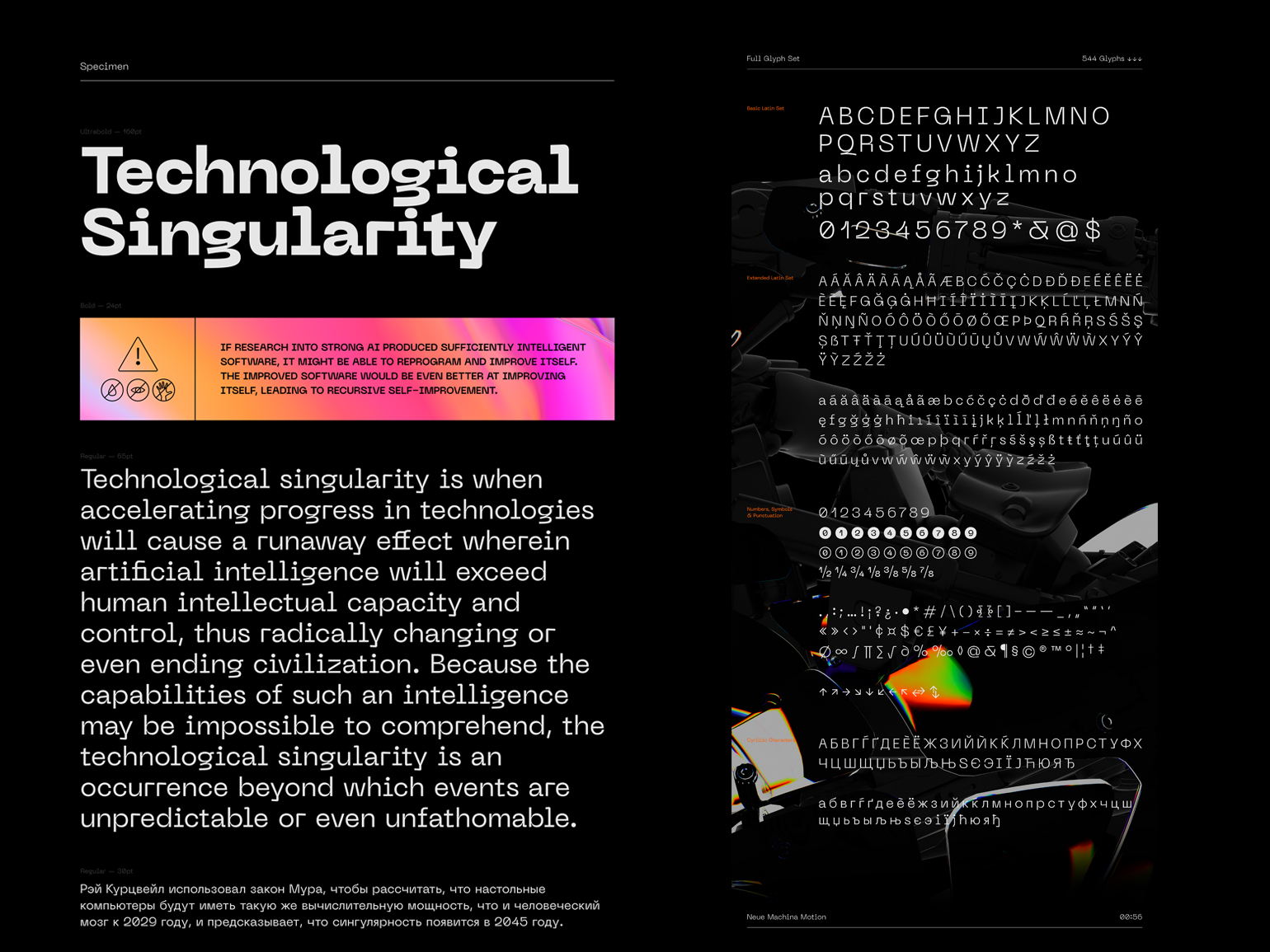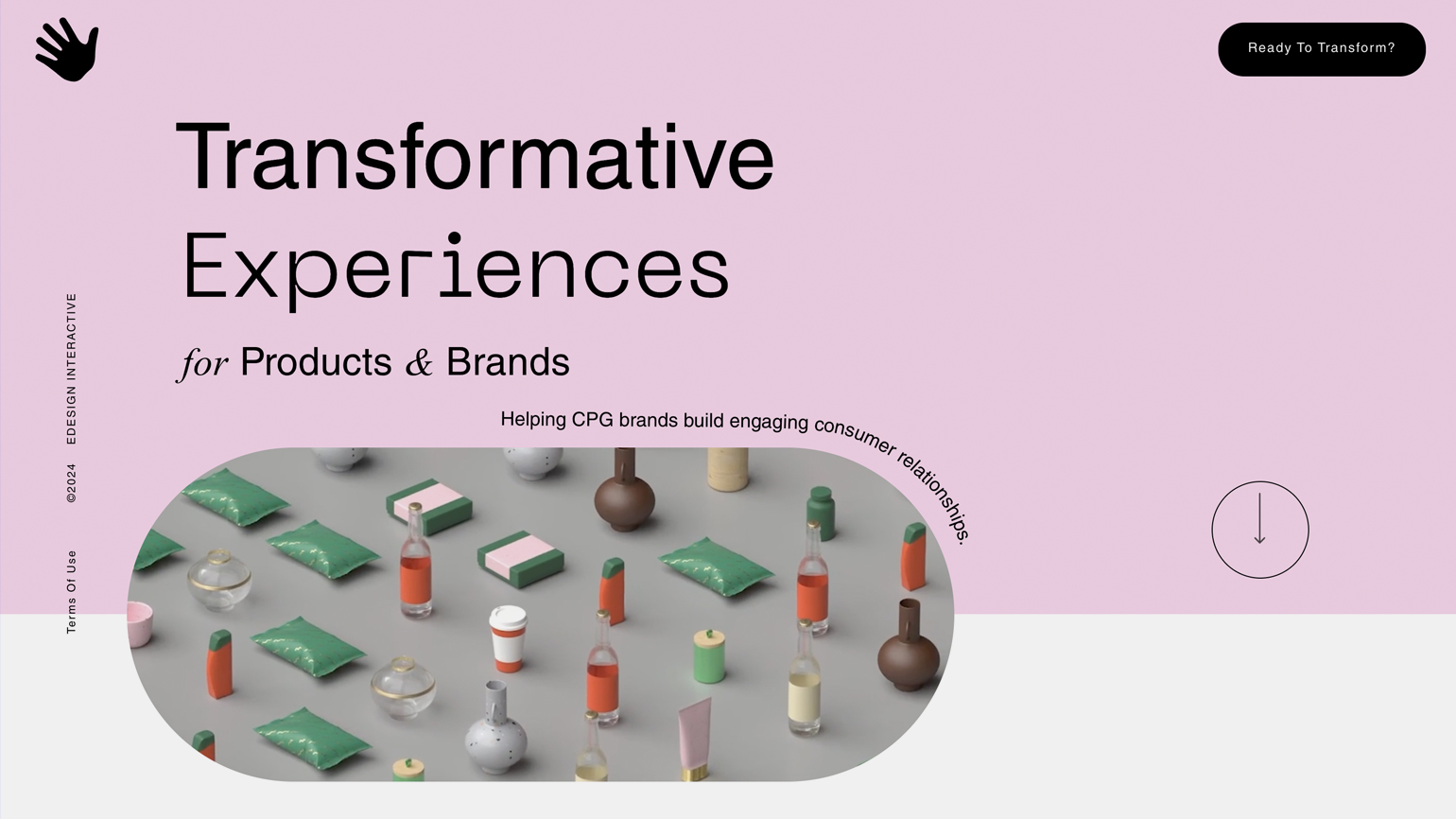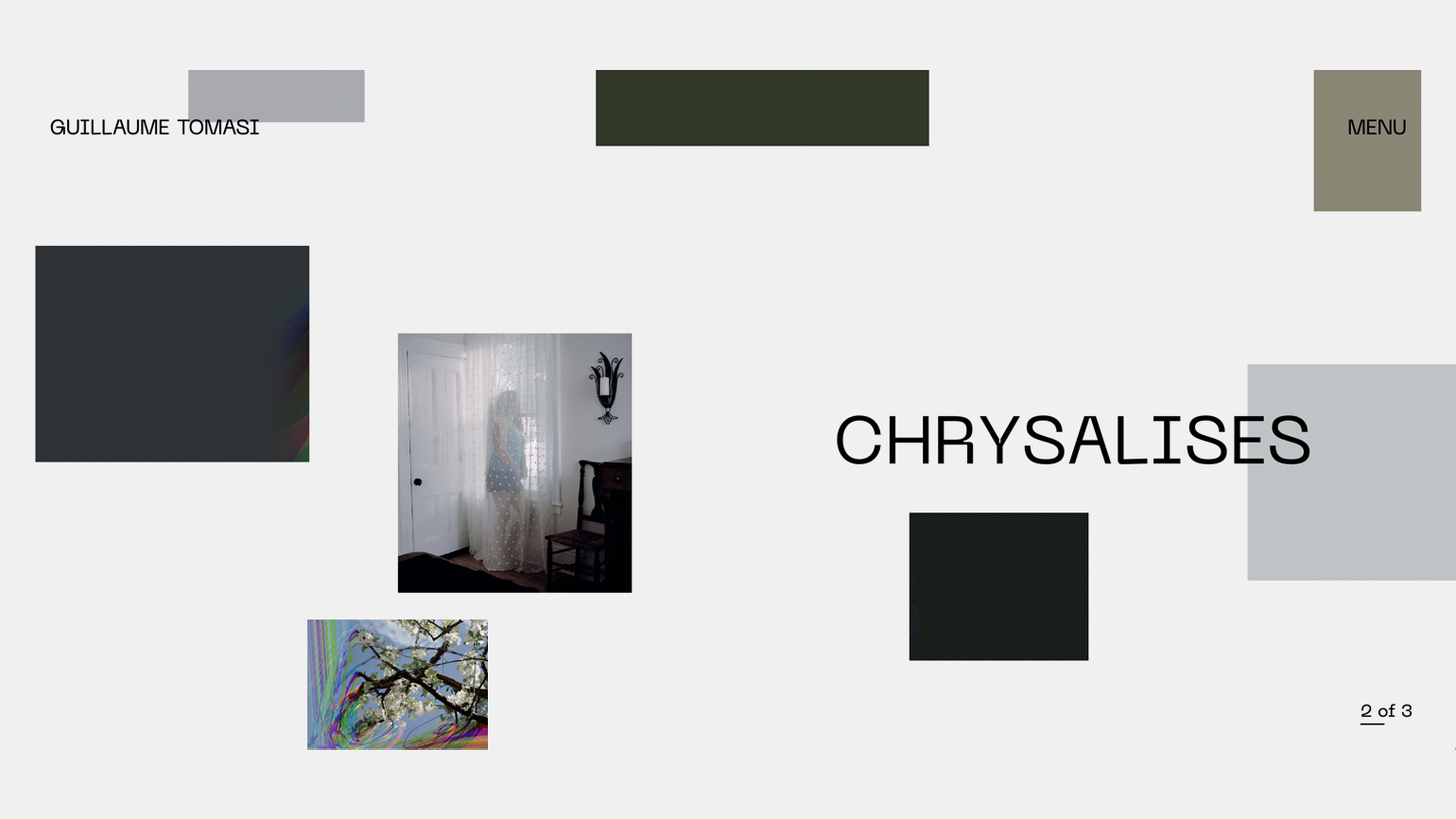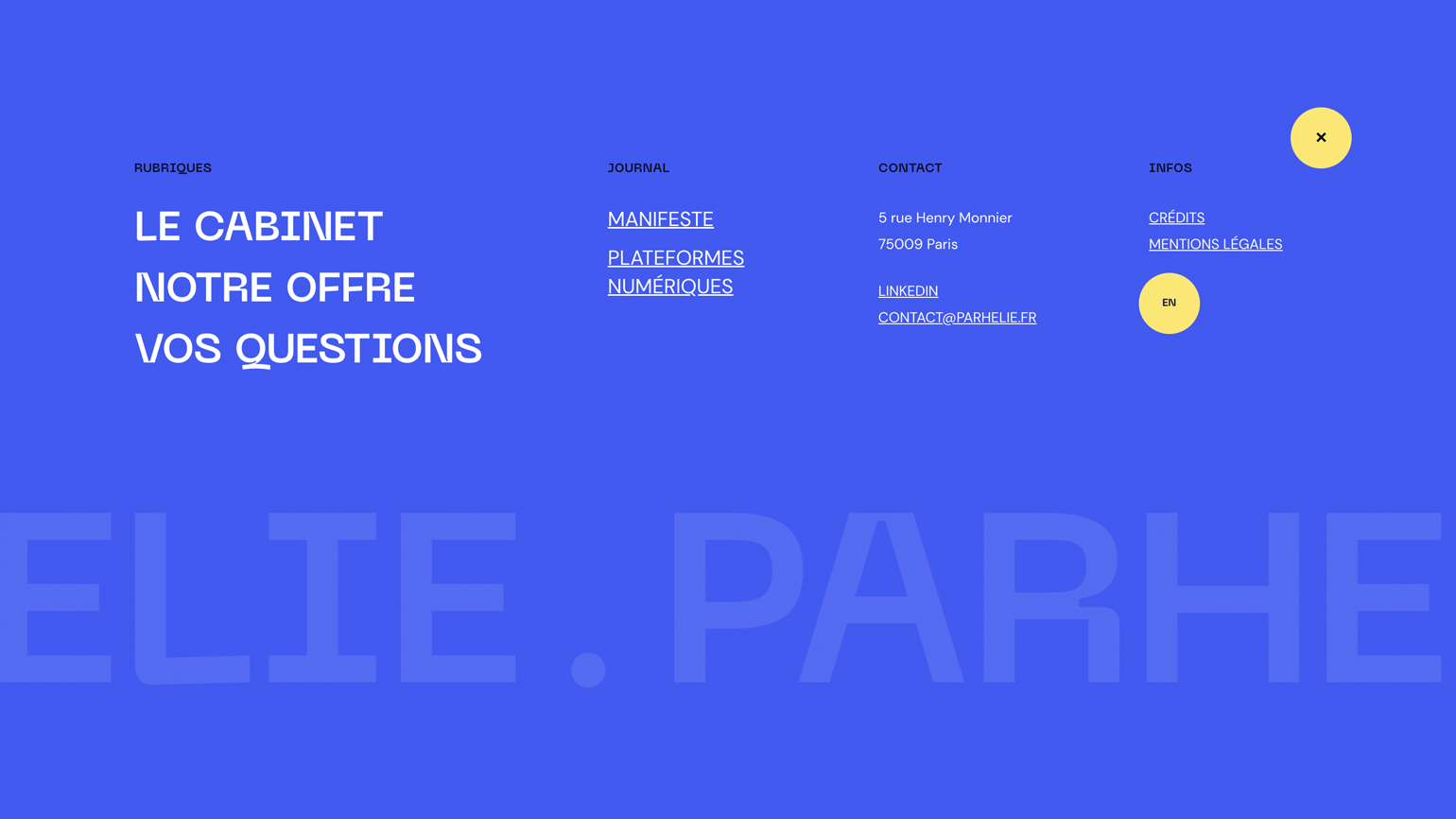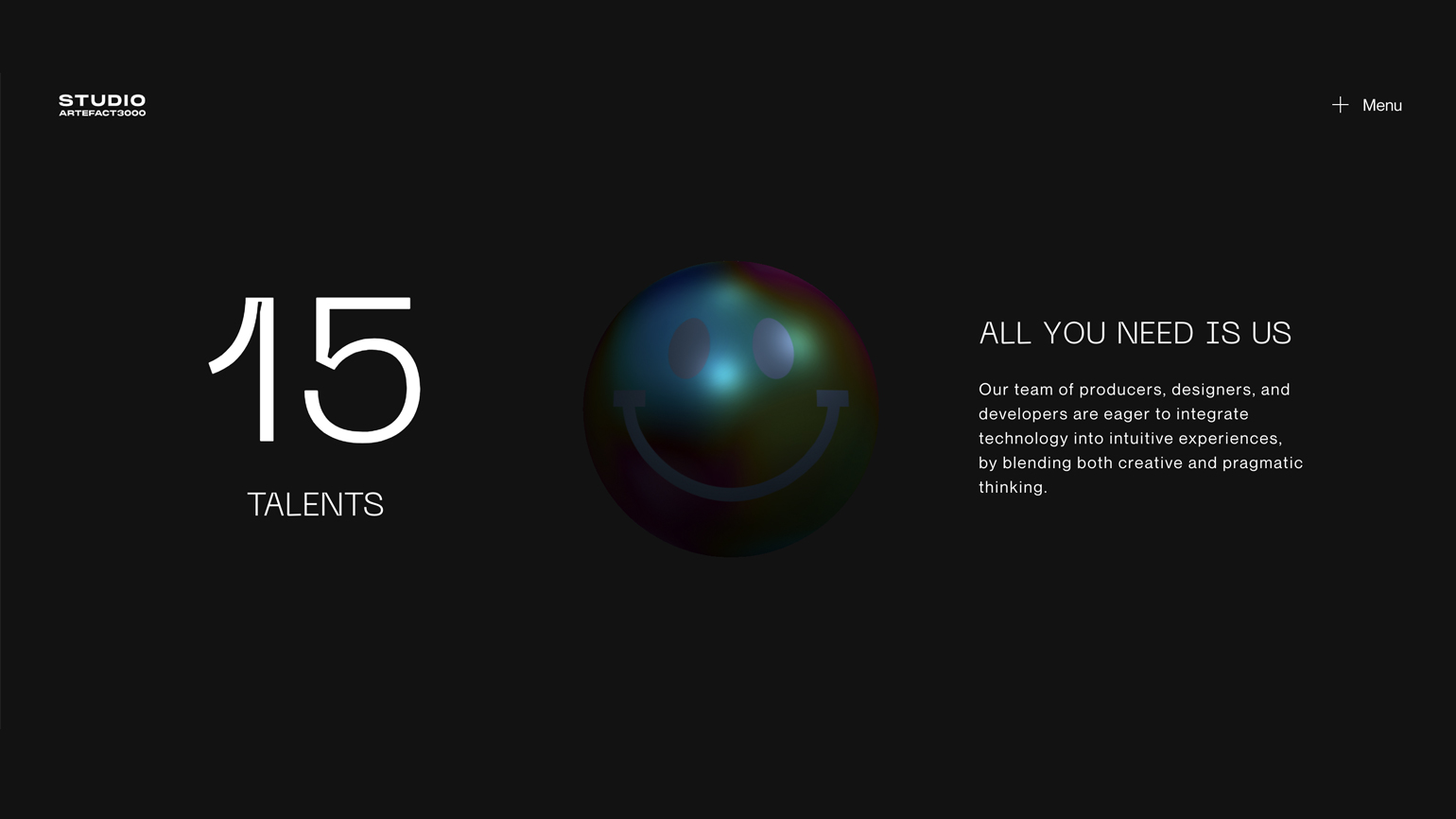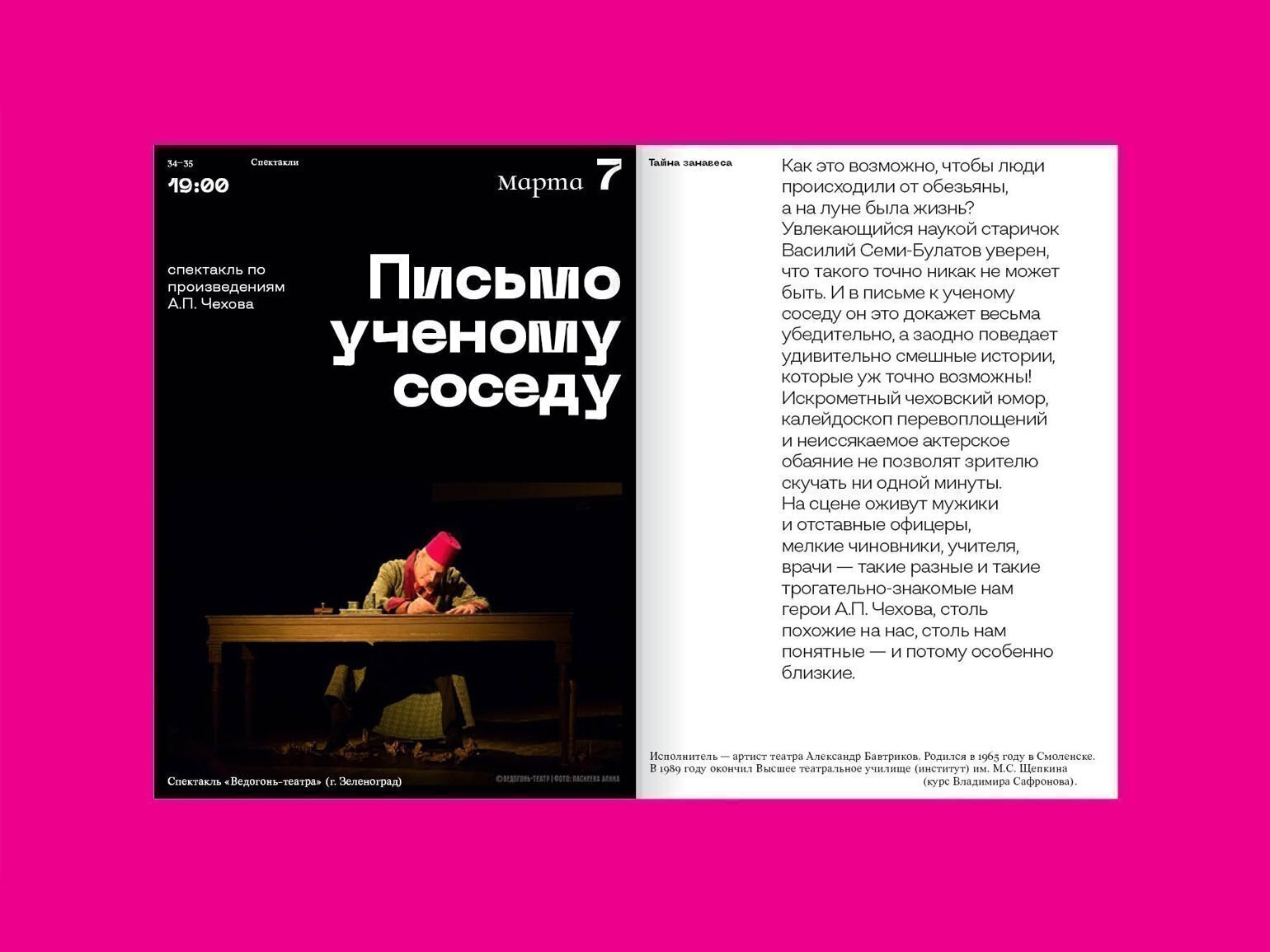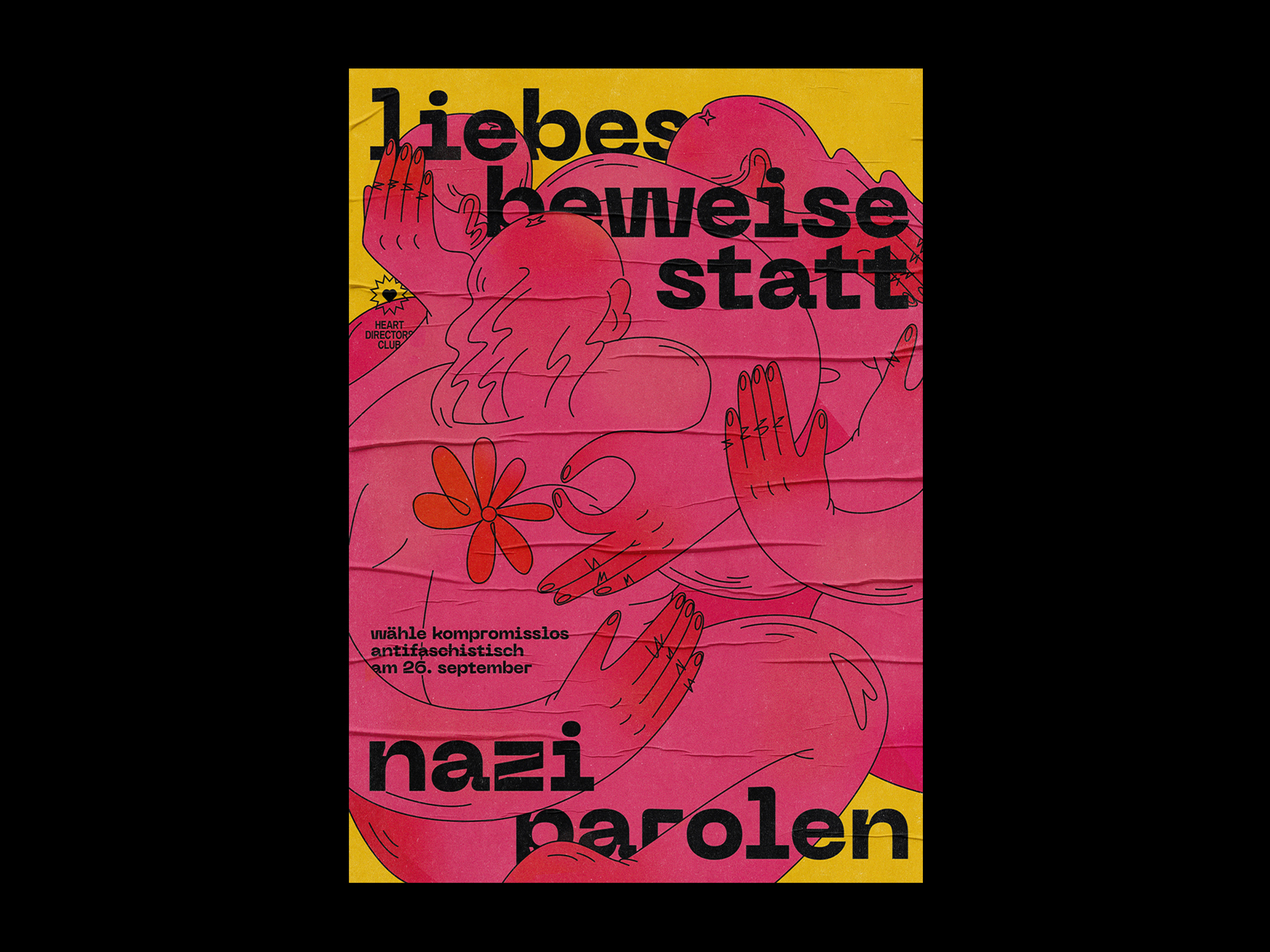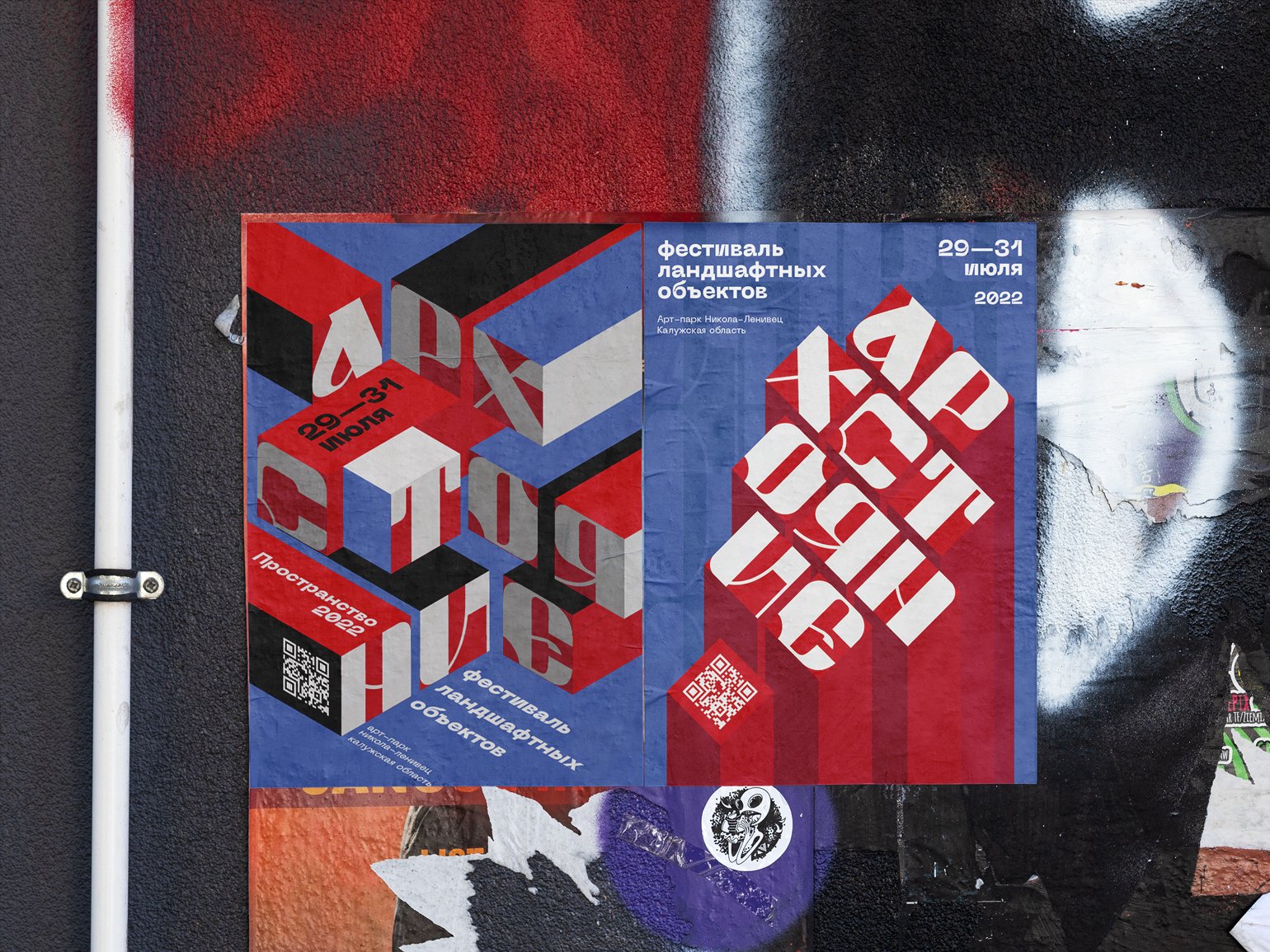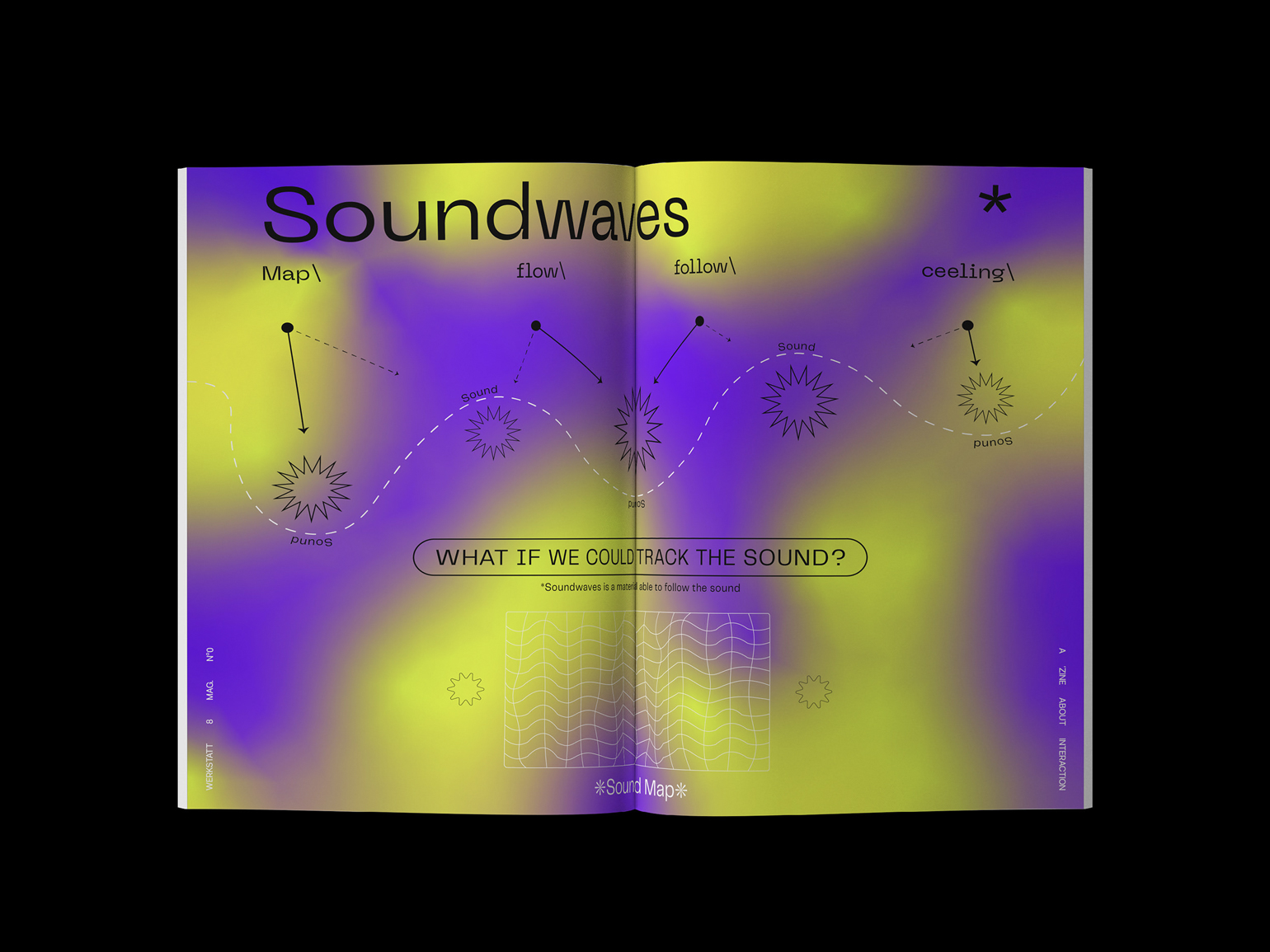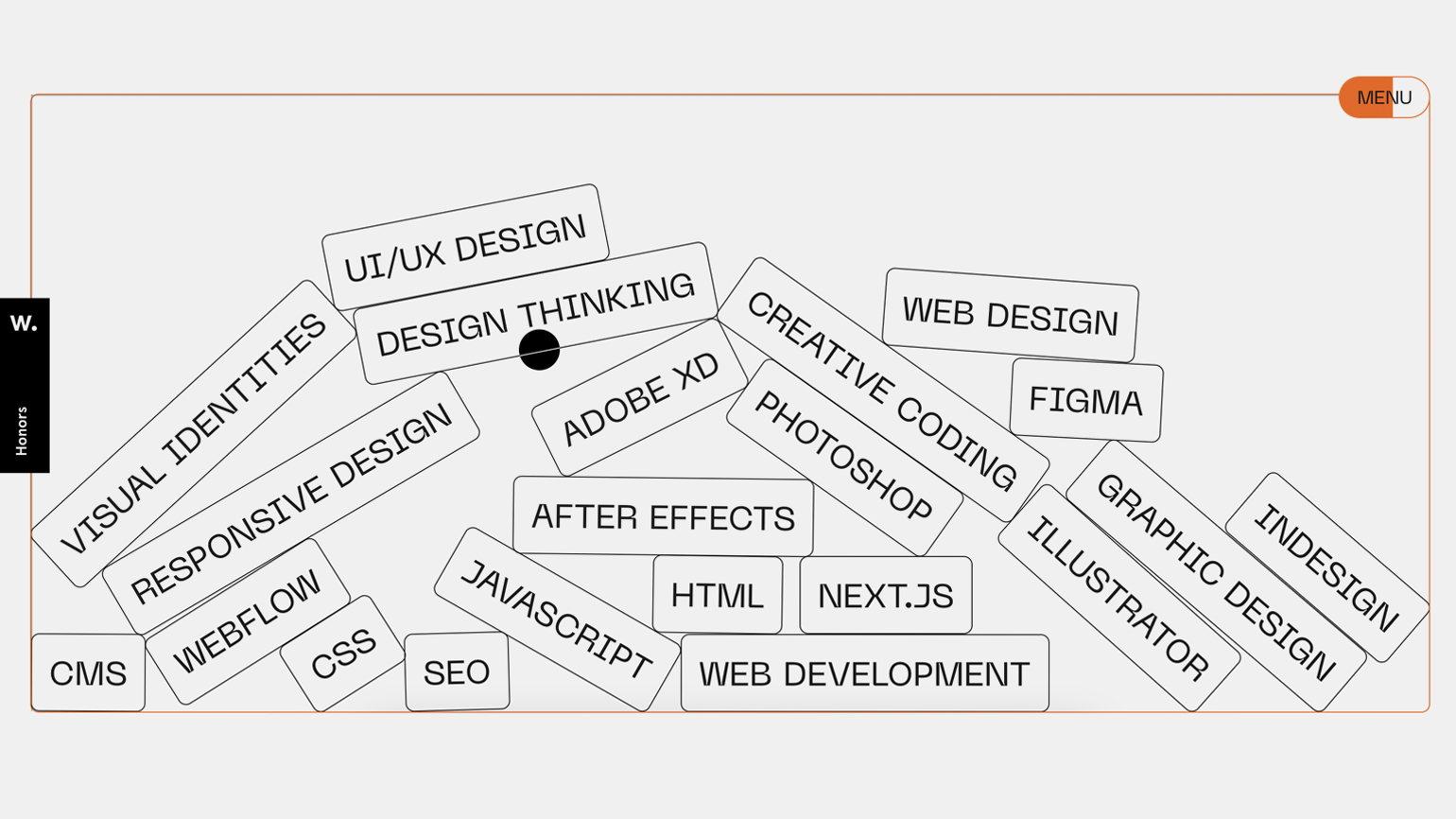
Шрифт Neue Machina: где используют и с чем сочетают
Рассказываем о трендовом шрифте и показываем примеры удачных шрифтовых пар с ним.
Neue Machina: что это за шрифт
Шрифтовое семейство Neue Machina выпустила студия Pangram в 2019 году. Её основатель и графический дизайнер Матьё Дежарден в интервью Илье Рудерману в 2020 году признался: когда он создаёт и подбирает в свою коллекцию шрифты, ориентируется на крупные тренды в поп-культуре и дизайне.
Neue Machina — тоже типографическая реакция на моду и прогрессивное искусство. Формально автор всех начертаний — Дежарден, но эти шрифты родились в коллаборации с известным современным цифровым художником и дизайнером Baugasm, который делился с Дежарденом своими мудбордами, идеями и видением.
В итоге Neue Machina стала суперсемейством из двух больших наборов:
• Inktrap Family — акцидентные гротески с явно заметными «ловушками чернил»;
• Plain Family — гротески с более спокойным характером.
Главными дизайн-референсами для Neue Machina, «Новой машины», были технологии будущего, роботы и тяжёлая техника.
Inktraps, ловушки для чернил или компенсаторы — это специальные «ямочки» в местах соединения штрихов в буквах. Исторически такие маленькие вырезы делали на литерах, чтобы краска при печати не заплывала и буквы оставались хорошо считываемыми даже в мелком размере и на рыхлой бумаге. Также ловушки позволяли сократить расход краски.
Сейчас inktraps — это в первую очередь декоративная деталь, визуальный референс к эпохе индустриализации и технического прогресса.
Знаковый набор Neue Machina. Кириллицу рисовал Матьё Дежарден, а проверял её дизайнер русского происхождения Алекс Слобженинов
Типографические постеры художника Baugasm, 2017 год
У всех шрифтов Neue Machina есть ярко выраженный визуальный характер. В них есть строгая геометрия, буквы одновременно с высокими контрастами в штрихах и малоконтрастные, знаки-механизмы и элегантные элементы. Например, W напоминает четыре сложенных рядом бруска, а благодаря ямочкам в d или b кажется, что они выведены пером.
Эстетика Neue Machina в студенческом проекте
Neue Machina идеально подходит для современного цифрового дизайна
Шрифты семейств Neue Machina часто используют в дизайне портфолио разработчиков, сайтов для стартапов, новых финансовых сервисов.
Neue Machina в дизайне интернет-медиа для цветных американцев-зумеров
В 2022 году в студии Pangram доработали и обновили Neue Machina. Актуальная версия — это:
• Два семейства, в каждом по девять начертаний от Thin до Black и девять соответствующих курсивов плюс файлы вариативных шрифтов.
• Расширенная латиница и кириллица.
• Лигатуры и альтернативные знаки.
Кириллица Neue Machina. На цветных формах слова набраны IBM Plex Sans
Теперь посмотрим примеры дизайна с Neue Machina и какие шрифтовые пары с ним можно составлять.
Neue Machina в интерфейсах
Для сайта студии цифрового дизайна выбрали пару из Neue Machina Inktrap и Neue Montreal. Первый работает как акцидентный: заголовки и выносы набраны шрифтом в начертании Light, но в крупном размере, поэтому декоративные ловушки для чернил хорошо заметны и привлекают внимание к тексту.
Neue Montreal тоже продукт студии Pangram Pangram. Дежарден создал этот нейтральный гротеск как собственную «гельветику», рабочую лошадку для цифрового дизайна.
Шрифтовая пара Neue Machina и Neue Montreal
Онлайн-магазин азиатских продуктов оформлен достаточно нестандартно: в дизайне минималистичная палитра, лаконичные карточки товаров, и вместо шрифтов в «японском» стиле использованы Neue Machina в разной насыщенности. Такая типографика помогает позиционировать площадку как сервис для молодых, состоятельных эстетов, которые любят экспериментировать с новыми вкусами.
Однако в масках полей тексты-подсказки набраны нейтральным и доброжелательным Montserrat. В светлом цвете и тонком начертании его легче считывать, чем харáктерный Neue Machina.
Шрифтовая пара Neue Machina и Montserrat
Лендинг юридической фирмы, которая специализируется на налоговых вопросах, оформлен яркими цветами и парой из механистичных Neue Machina и DM Sans. Такой дизайн транслирует: эта команда точно разбирается в юридических тонкостях, которые актуальны для современных цифровых бизнесов.
Шрифтовая пара Neue Machina и DM Sans
На сайте сервисной компании, которая работает на B2B-рынке, дизайнеры использовали микс из трёх разных по графике шрифтов: Neue Machina, курсив Times New Roman и Helvetica. Сделать такую смесь гармоничной сложно, но подобная яркая типографика точно привлечёт внимание и выделит интерфейс среди сотен других.